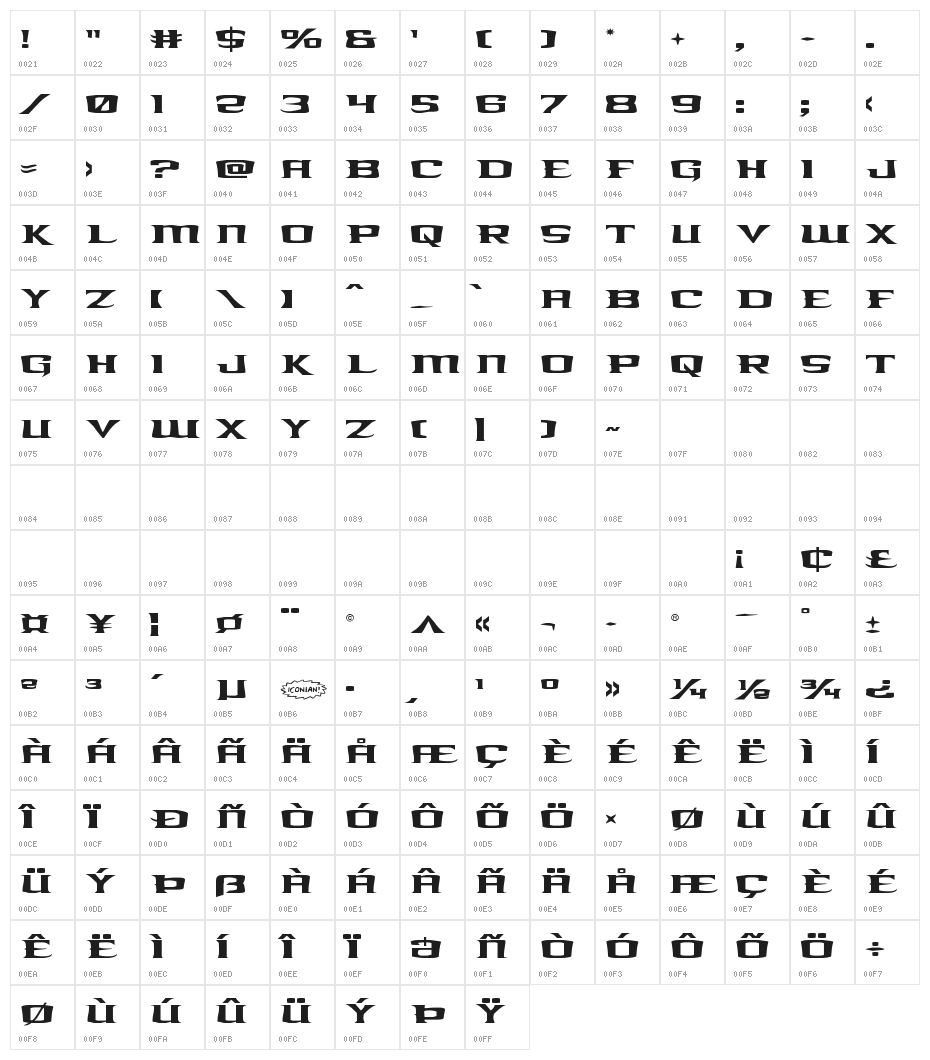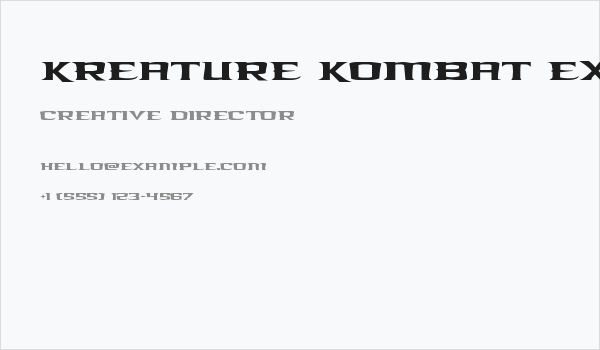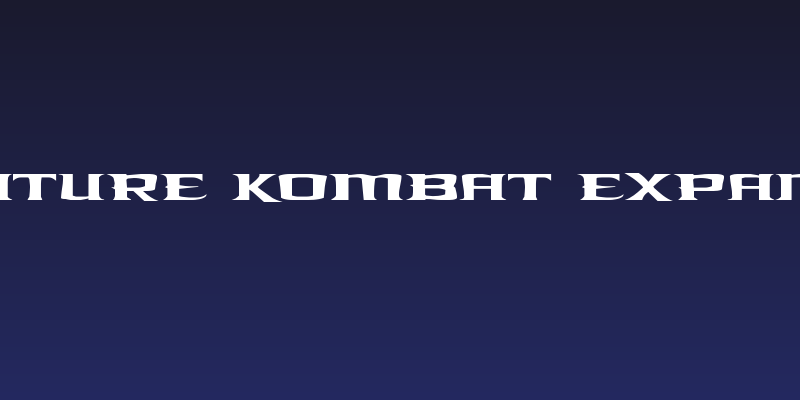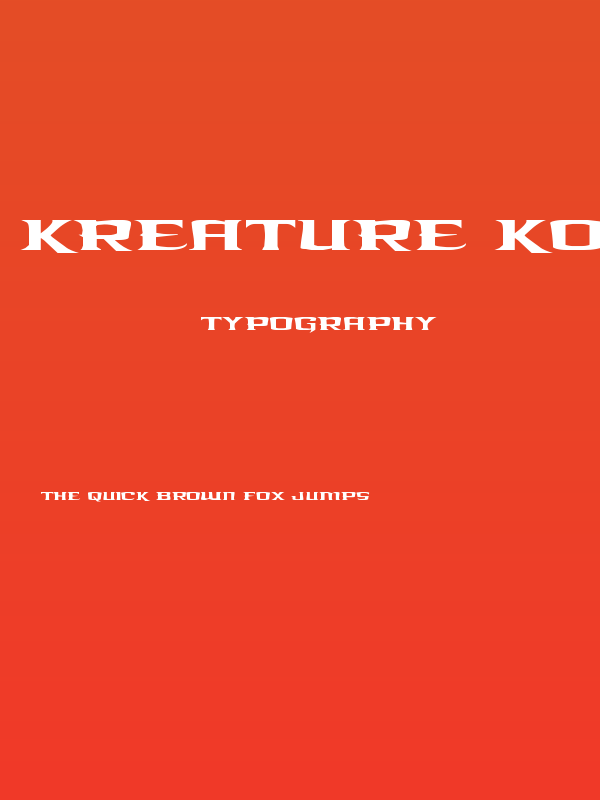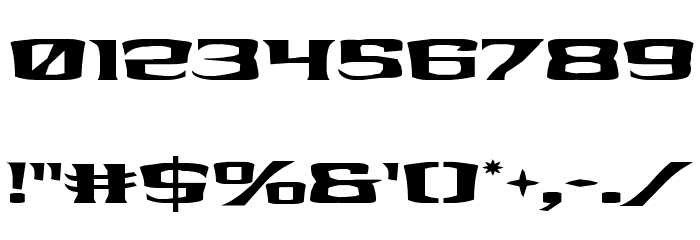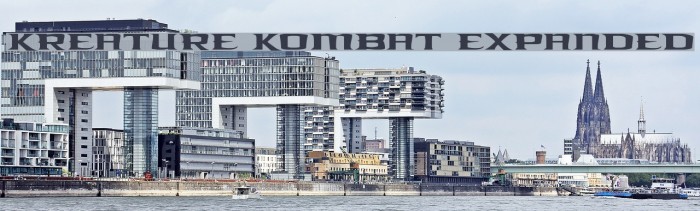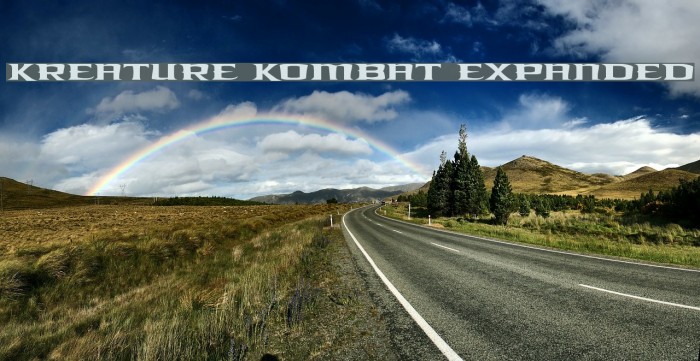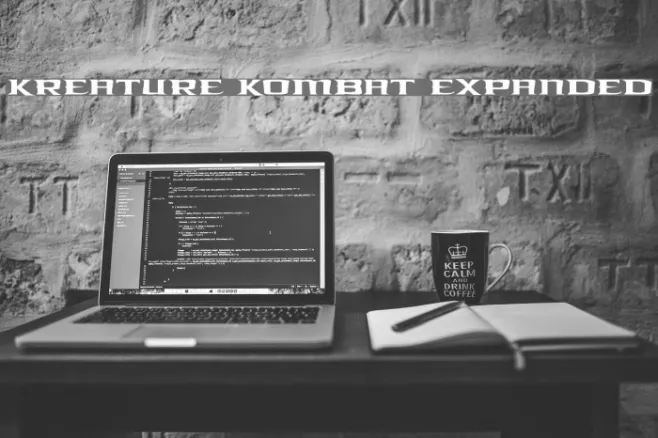
Kreature Kombat Expanded Font
| Estilo general | Modern, Edgy |
| Proyectos propuestos | Ideal for video game titles, sports team logos, action movie posters, or any project requiring a strong and edgy visual impact. |